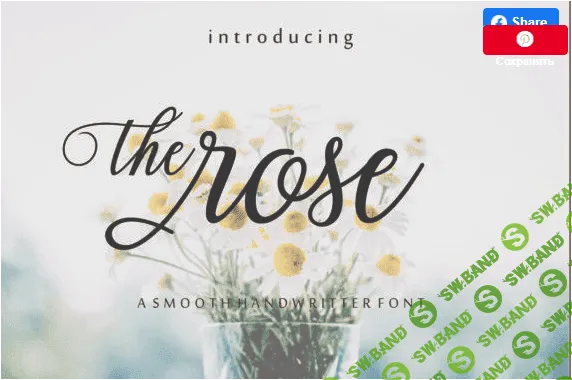
Название: The Rose Script Font (2022)
The Rose — это гладкий рукописный шрифт. Каждая буква была тщательно обработана, чтобы придать вашему дизайну элегантный вид.
Он идеально подходит для свадеб, приглашений, поздравительных открыток, плакатов, визитных карточек, цитат, заголовков блогов, брендинга, логотипов и любого другого дизайна, требующего роскошного ощущения.